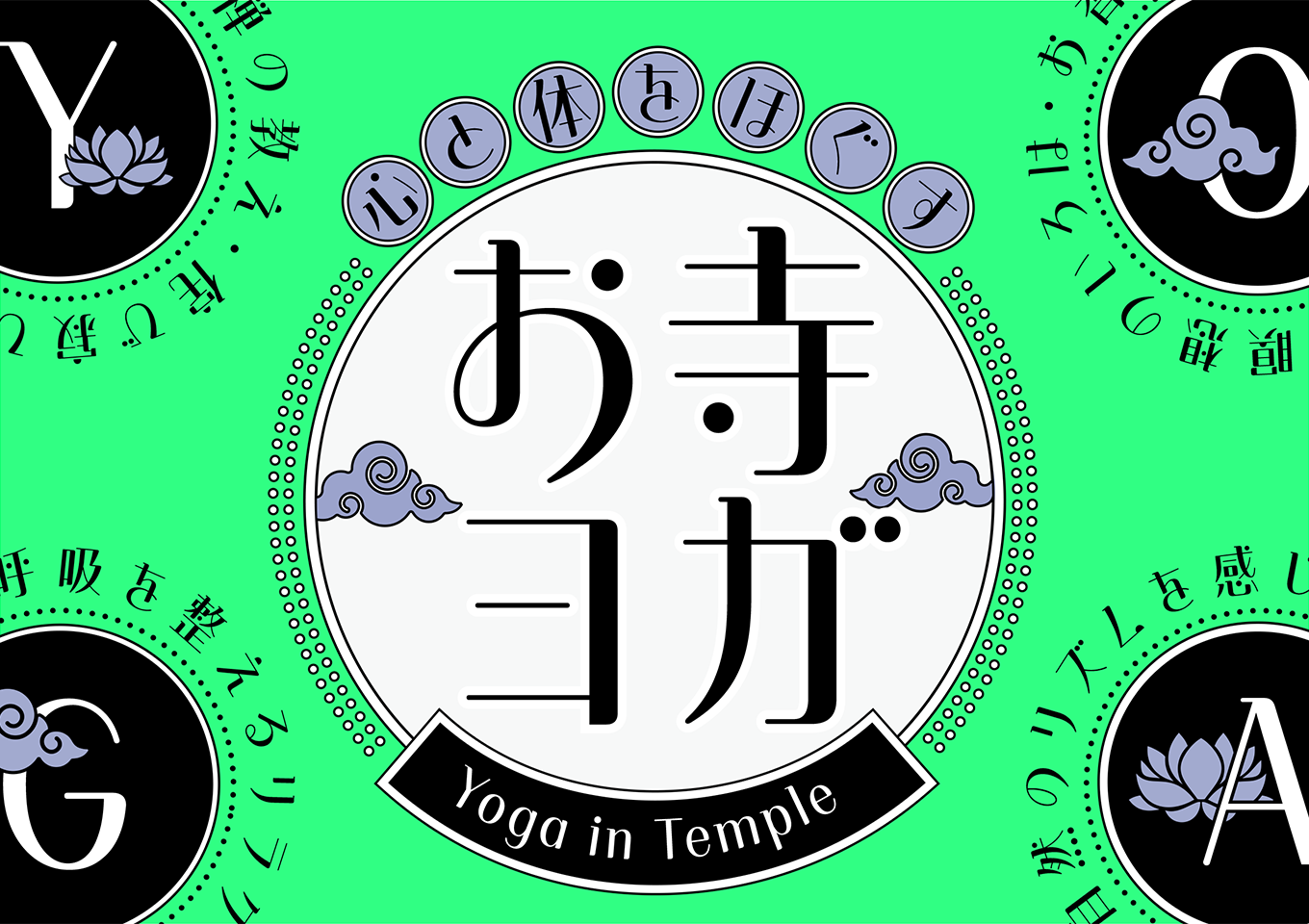
モダンで可愛らしい印象のハイコントラストなデザイン書体です。長体ぎみのプロポーションと極細の横画やハライの繊細な印象に加えて、円や半円の点が遊び心を感じさせます。ロゴやコピーなど、アイキャッチとしての利用で存在感を発揮します。なお、本書体はモリサワで制作したかな・英数字に、Arphic Typesの「AR白玉書体」の漢字を組み合わせています。